Le vintage est à la mode, depuis toujours et pour toujours ! Face à un tel engouement, il peut s’avérer utile d’avoir à sa disposition une sélection de typographies vintage à tester dans vos créations, qu’il s’agisse de logos, d’affiches, de packagings ou même de T-shirts. Pour aller plus loin, n’hésitez pas à consulter notre article pour vous aider à choisir le type de typographie qu’il vous faut.
Pour l’heure, voici les 15 typographies vintage à télécharger gratuitement en vue de projets !
Bilderberg
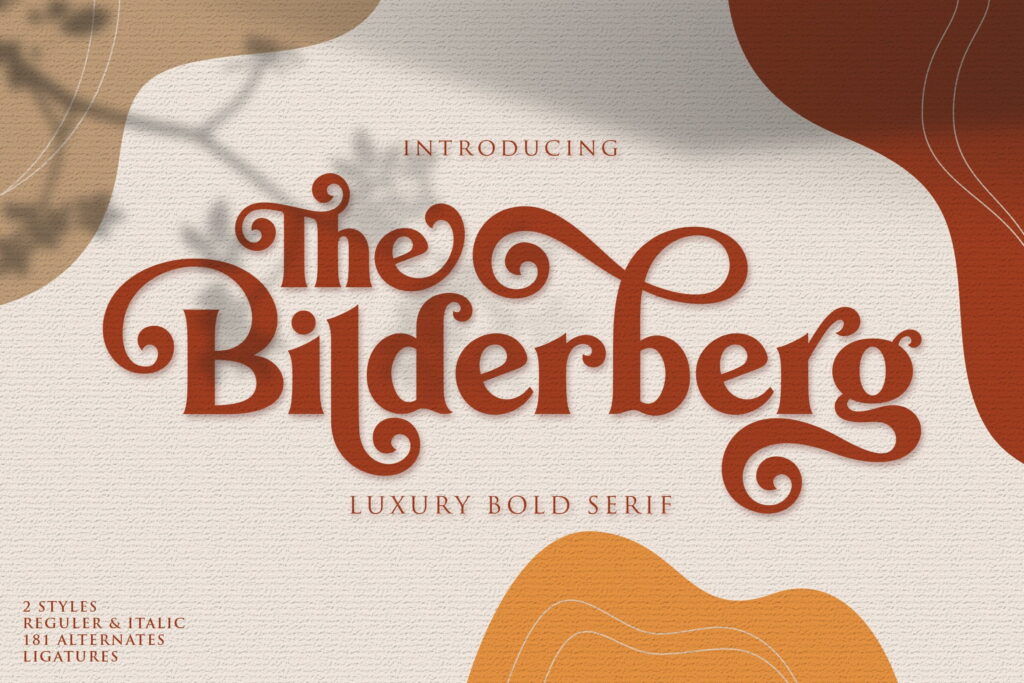
Une serif élégante au charme rétro, idéale pour titres et branding sophistiqué.
Magic Retro
Vintage et renvoyant une image particulièrement tendance, la typographie Magic Retro accompagnera parfaitement les projets où vintage et originalité doivent aller de pair.
Keep on truckin
Une police psychédélique emblématique des années 70, pleine de fun et de personnalité, idéale pour un look rétro affirmé.
Cooper Black
Son style audacieux et légèrement “cartoonesque” lui confère un look vintage unique, souvent associé aux années 60-70, au pop art et à la publicité old-school. Cooper Black combine lisibilité et personnalité, ce qui en fait un choix intemporel de typographie vintage à la fois fun et impactant.
Retro Groovy
Une typographie vintage audacieuse aux formes arrondies et funky, idéale pour des titres et visuels au style vintage affirmé.
Boomtown Deco Free font
Une police inspirée de l’Art Déco, aux lettres élancées et stylisées, parfaite pour des titres ou logos avec une touche rétro moderne
Vintage style
Vous avez un projet au style nostalgique ? Vintage style est une typographie rétro au look classique et affirmé, parfaite pour titres, affiches.
Vintage font
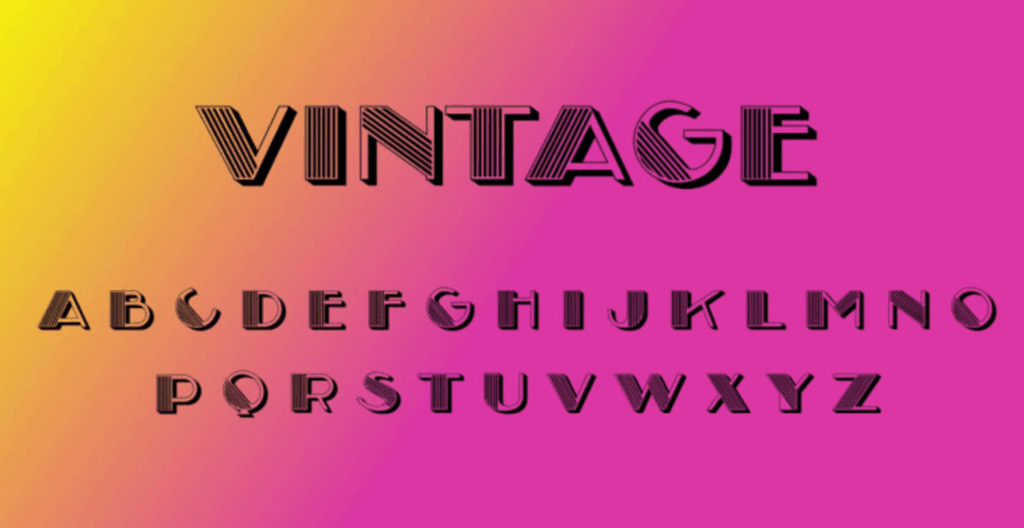
Une typographie display au look rétro authentique, idéale pour titres et projets graphiques au style classique et nostalgique.
Lazer 84
Si vous cherchez une police rétro qui rappelle bien les années 80 et le style néon, Lazer 84 conviendra parfaitement à votre projet.
Neon spooky
Une typographie rétro qui reproduit l’effet lumineux du néon, idéale pour des titres et visuels percutants.
Retroking
Une police vintage audacieuse, parfaite pour donner du caractère à vos projets créatifs. On l’imagine particulièrement dans vos vidéos, comme par exemple un générique de film.
Antique Book Cover
Imitant un lettrage à la main, cette police s’intégrera parfaitement à un très grand nombre de projets de créations graphiques vintages.
Retro club
Retro Club est une police rétro au design stylisé et affirmé, idéale pour donner une allure vintage percutante à vos titres, affiches ou projets graphiques.
Eighties
Eighties : une police rétro pleine de caractère, parfaite pour un style vintage dynamique et affirmé.
Pompadour Numerals
Vous désirez afficher sur vos créations des chiffres qui ne ressemblent à aucun autre ? Pourquoi ne pas vous tourner vers la typographie Pompadour Numerals ? S’inspirant des coiffures « Rockability » des années 1950, ces chiffres fonctionnent à merveille lorsqu’ils sont utilisés en grande taille !
FAQ
Comment reconnaître une typographie vintage ?
Les typos vintages ont généralement un design orné et élaboré, avec des sérifs détaillés.
Elles sont souvent très épaisses, ce qui leur donne un look puissant et majestueux. Les typos vintages peuvent avoir des effets de vieillissement comme des taches ou des traits de crayon.
Les typos vintages ont aussi une histoire ou une signification particulière. Certaines sont même célèbres ! Si vous avez du mal à trouver une typo vintage, n’hésitez pas à demander de l’aide à un expert en design graphique. Il sera probablement en mesure de vous fournir une liste de polices qui pourraient correspondre à votre projet.
Qu’est-ce qui caractérise une police vintage ?
Une typo vintage a une apparence ancienne ou usée. Elle peut être utilisée pour imiter le style des années 20, 30, 40 ou 50. Les polices vintages ont généralement des talons arrondis, des sérifs épais et des ornements détaillés. Si vous cherchez à donner à votre marque une touche rétro, une typo vintage est une excellente option. Assurez-vous simplement de bien la choisir pour qu’elle corresponde à l’esthétique que vous recherchez.
Pourquoi les typographies vintages ont-elles toujours la cote ?
Il y a quelque chose de spécial à propos des polices vintages qui sont si appréciées des designers et des créateurs de contenu. Peut-être est-ce leur caractère unique et leur capacité à donner un sentiment de nostalgie ou d’élégance classique… Quoi qu’il en soit, il est facile de voir pourquoi les polices vintages font partie intégrante du design moderne.
Les typos vintages ont généralement une histoire et une âme, ce qui les rend plus intéressantes que les polices standards. Les polices vintages parlent d’elles-mêmes, sont élégantes et parfaites pour tout projet exigeant un peu plus de style et de substance.